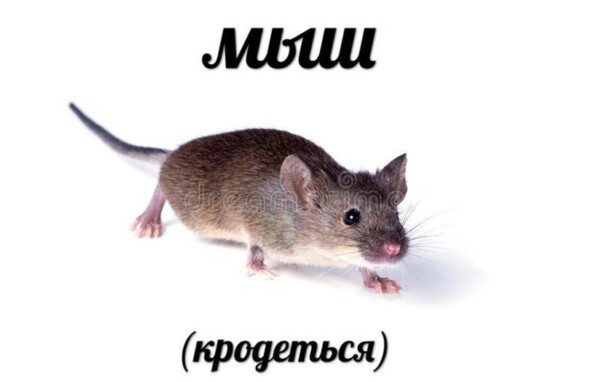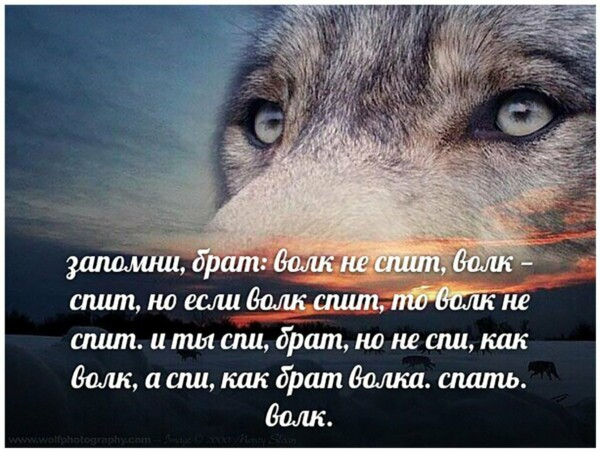
В рунете сложилась уникальная ситуация, где у главного «мемного» шрифта Impact есть конкурент. Повлияло отсутствие альтернатив в старой версии фоторедактора «ВКонтакте».
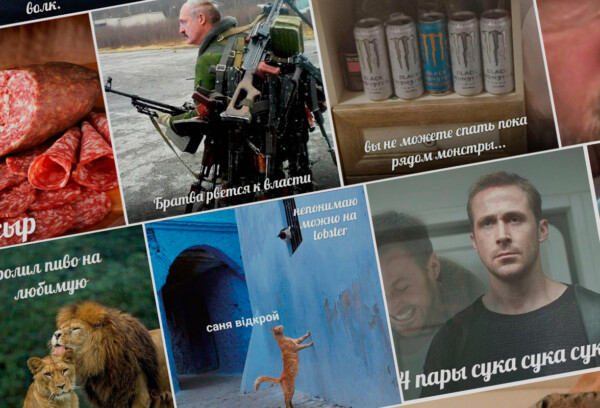
Если людям со всего мира задать вопрос, какой шрифт они ассоциируют с мемами, то первым ответом, вероятно, будет Impact. В 1996 году он вошёл в проект Microsoft по определению «основных шрифтов интернета» (Core fonts for the Web), затем стал главным шрифтом на сайтах-генераторах картинок и в начале «нулевых» превратился в своеобразный стандарт для подписей к мемам.
Второй кандидат — Comic Sans, один из самых ненавистных шрифтов интернета. И только в русскоязычном пространстве может возникнуть вариант Lobster: он был довольно популярным десять лет назад, но теперь считается устаревшим и ставшим жертвой собственной узнаваемости. Но в рунете у него своя жизнь: если в начале «десятых» картинки с этим шрифтом считались чем-то обычным, то сейчас Lobster — явный признак постироничного мема, которых в соцсетях полно.
TJ разобрался, как Lobser прошёл такой путь и причём тут фоторедактор «ВКонтакте».
* * *Шрифт в 2010 году создал аргентинский дизайнер Пабло Импальяри (Pablo Impallari), в том же году Lobster вошёл в библиотеку Google Web Fonts. В интервью аргентинец объяснял: «Я хотел создать неформальный курсивный шрифт, который выглядел бы одновременно разборчиво и дружелюбно. Есть ситуации, в который Arial и Times New Roman выглядят скучно. Неформальные приглашения, флаеры для вечеринок, открытки — вы и сами всё знаете».
Lobster сразу же оказался крайне популярным — его использовали повсюду. Поначалу дизайнеры его хвалили: «Винтажный, но не классический, забавный, но не глупый». В 2019 году дизайнер Ник Хилтон в своём блоге на Medium рассказывал, как шрифт «завоёвывал» Лондон: по его мнению, это было связано с сочетанием стиля и доступности — лицензия позволяла использовать его даже «самым скупым владельцам бизнеса». Но в то же время Lobster появлялся и у крупных брендом вроде «Макдоналдса».
«Импальяри создал этот шрифт в 2010 году, а потом просто ушёл. Его сайт сейчас мёртв, но его работа продолжила жить по всему миру», — отмечал Хилтон.
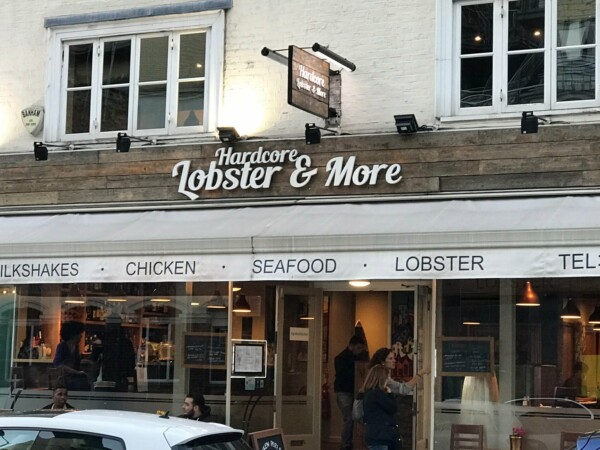
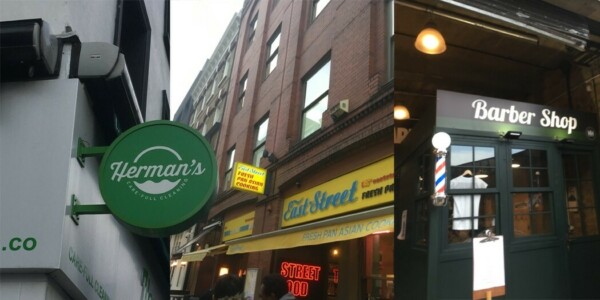
Такая популярность шрифта к очевидному итогу — уже пару лет спустя Lobster стал постоянным героем подборок вроде «Шрифты, которые вам нужно перестать использовать прямо сейчас». Дизайнеры стали стыдить коллег за работы с ним и предлагать менее заезженные альтернативы. Причина такой нелюбви типична для «неклассических» шрифтов: они слишком узнаваемы, поэтому их излишнее использование сразу же бросается в глаза.
В 2014 году даже появился сайт «Lobster — новый Comic Sans», потому что последний тоже со временем стал объектом для насмешек. Сайт уже не доступен, но аналогичное мнение всё ещё в ходу.
Но только в русскоязычной среде Lobster стал не просто надоедливым шрифтом с вывесок и открыток, но и частью онлайн-культуры. Кириллическую версию шрифта в 2011 году создали дизайнеры Гаянэ Багдасарян и Алексей Ваняшин. Последний в то время был автором проекта Cyreal: вместе с 15 коллегами он занимался популяризацией кириллицы и общедоступных шрифтов.
В первые же месяцы Lobster втянули в политику: прокремлёвское движение «Наши» сделало календарь «Секс против коррупции» — его опубликовала в своём блоге Кристина Потупчик.
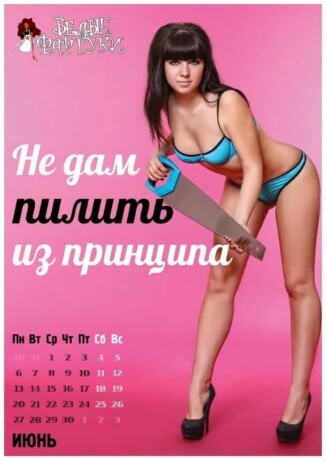
Но главная стадия популярности шрифта неразрывно связана с «ВКонтакте». 10 октября 2012 года в соцсети произошло значимое обновление — впервые появился встроенный редактор фотографий. Уже через неделю туда добавили функцию наложения текста. Если верить сообществу LIVE, то сначала пользователям предложили классический шрифт Impact, но на следующий день его по каким-то причинам поменяли на безальтернативный вариант — Lobster.
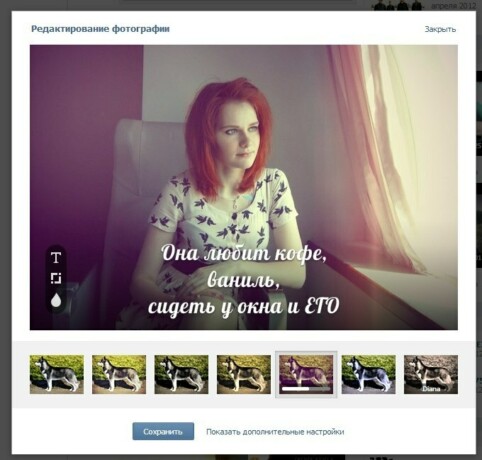
«Сейчас уже сложно вспомнить конкретные причины, которые привели к появлению Lobster в фоторедакторе. Думаю, что были они весьма прозаичны — мы взяли красивый по тем временам шрифт и использовали его», — отмечает в разговоре с TJ руководитель дизайна суперприложения «ВКонтакте» Илья Гришин.
Произошло это как раз во время расцвета разнообразных пабликов, и с появлением фоторедактора многие авторы стали делать картинки именно там. Соответственно, «ВКонтакте» наполнился изображениями с подписями шрифтом Lobster. Позже подключились и сайты-генераторы мемов, которые добавили шрифт в список стандартных.
Impact вернулся во «ВКонтакте» в июле 2013 года. Тогда русскоязычные мемы пришли к более классическому виду, но Lobster из соцсети не пропал — и в 2020 году его всё ещё можно найти в редакторе. Гришин отмечает: «Не будет преувеличением сказать, что миллионы людей делают мемы в нашем фоторедакторе. Так шрифт стал массовым и узнаваемым, а затем вышел за пределы VK — появились логотипы и вывески, в которых использовался Lobster. Он такой — новый Comic Sans поколения Z».
Но в последние годы Lobster — не обычный шрифт для подписи к картинке, а признак постироничного мема. В своё время «мемная» история Impact началась с изображения кота и фразы «I Can Has Cheezburger». В России же Lobster получил вторую жизнь не в последнюю очередь благодаря паблику «Мемы про котов (по ржать)».
За девять месяцев «Всратославом» воспользовались 300 тысяч пользователей, которые сгенерировали более 10 миллионов картинок. Бот, пожалуй, лучше всего показал, что в ироничных Lobster-мемах необязательна связь изображения и текста — юмористический эффект начинается уже с выбора шрифта.
В других странах Lobster не становился частью мемов — это уникальная черта рунета. Одного шрифта достаточно, чтобы понять — перед тобой постироничная картинка. Поэтому лучше использовать Lobster аккуратно, особенно, если хочется применить его в серьёзной ситуации.